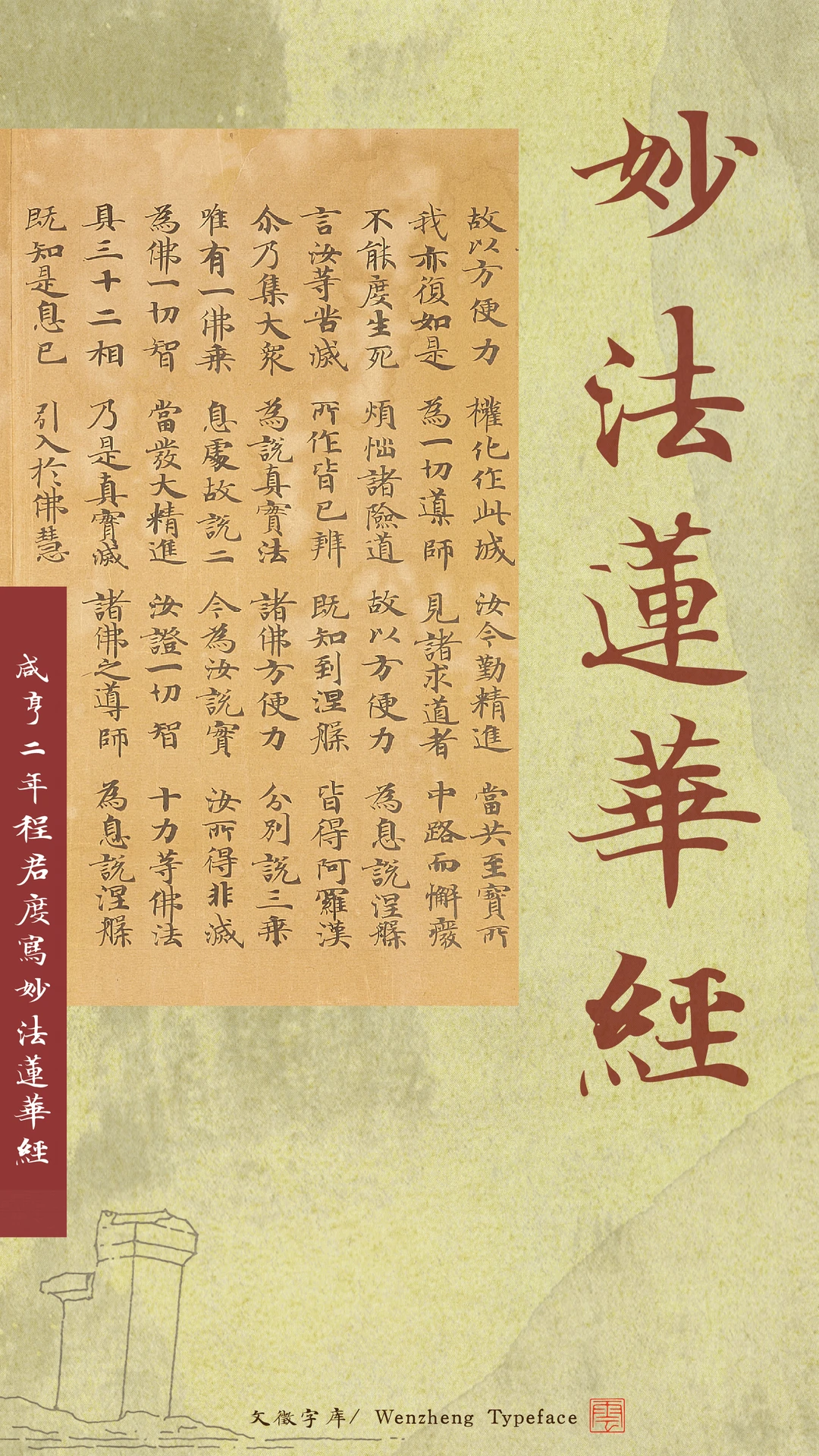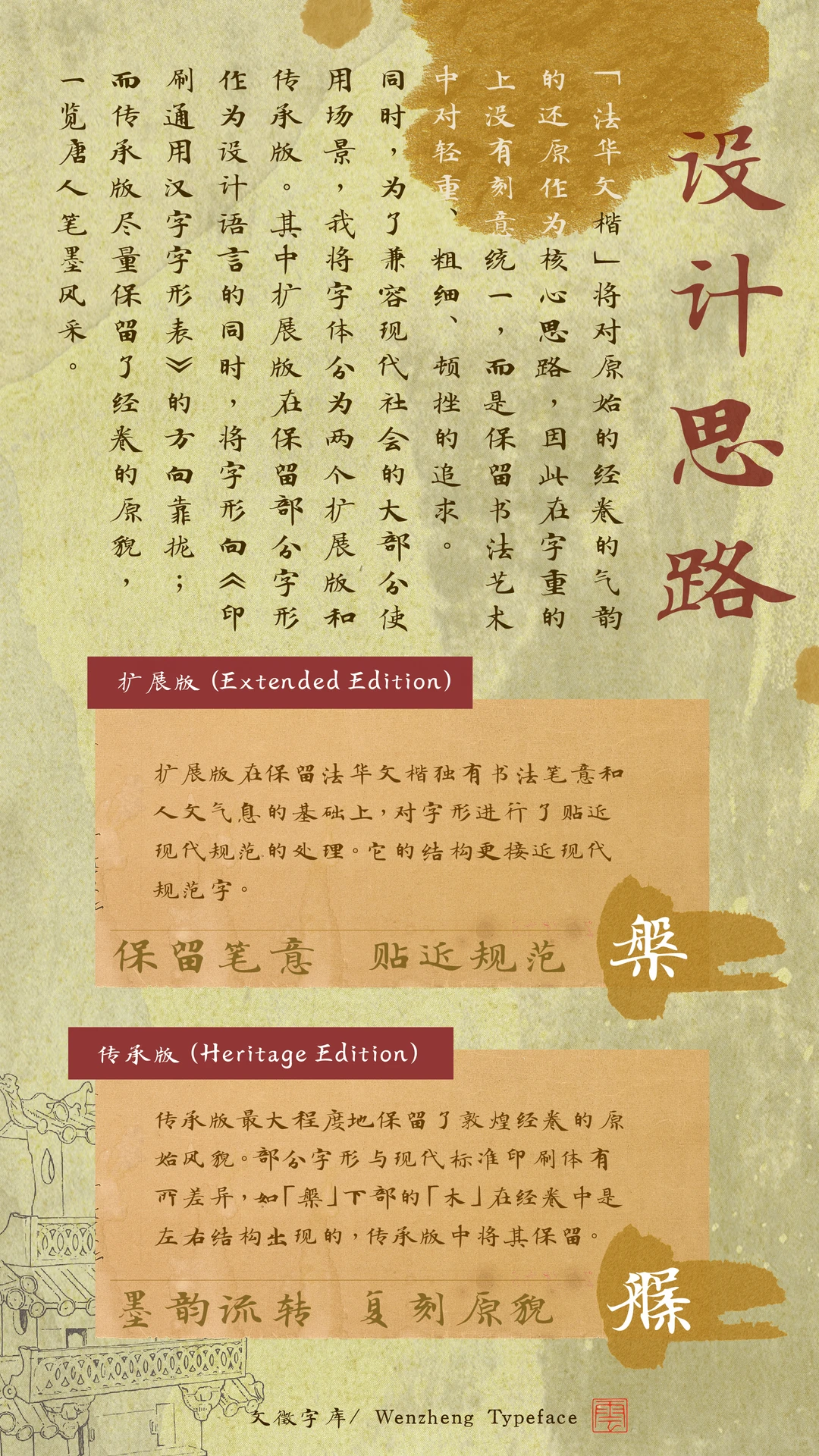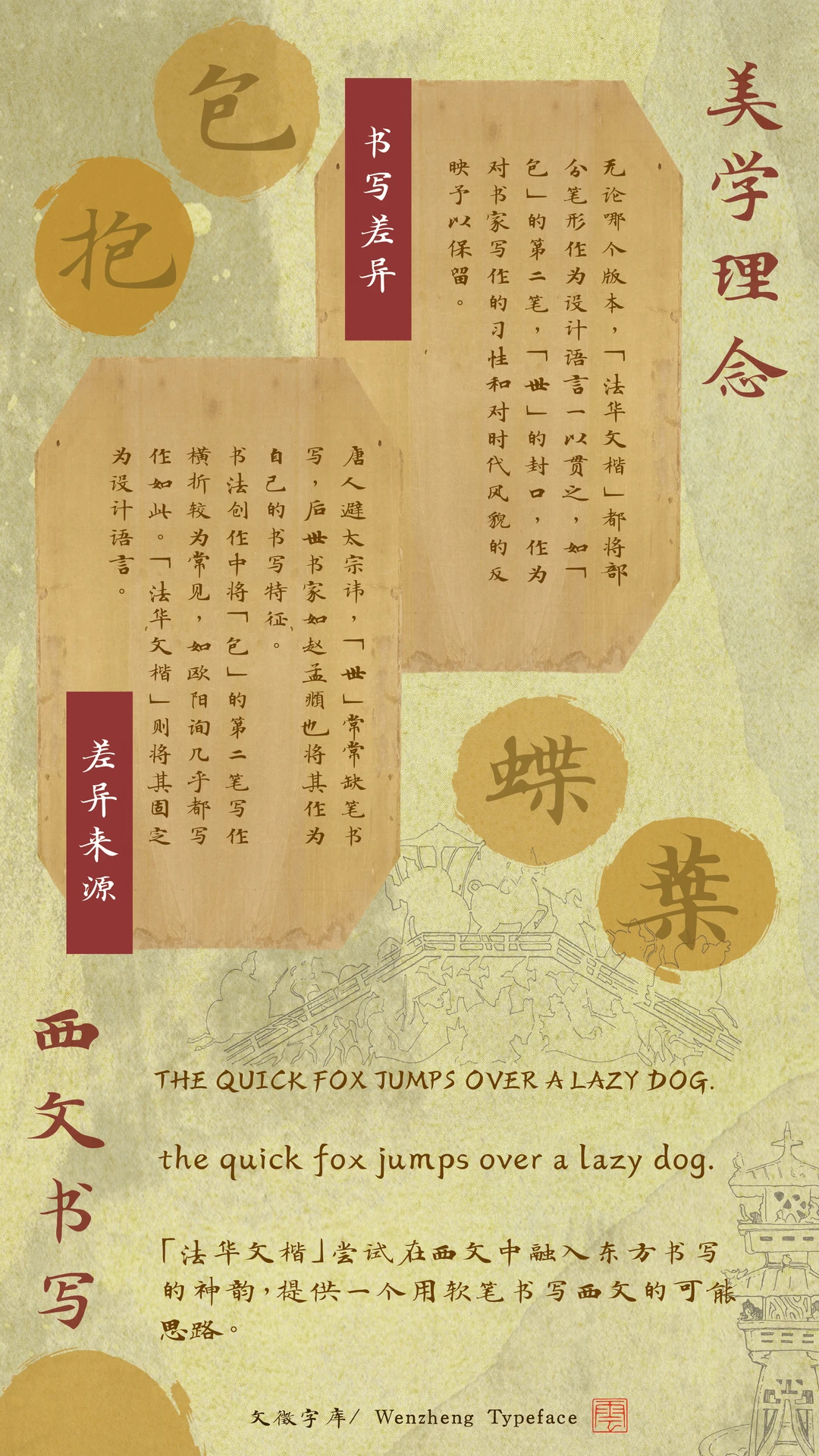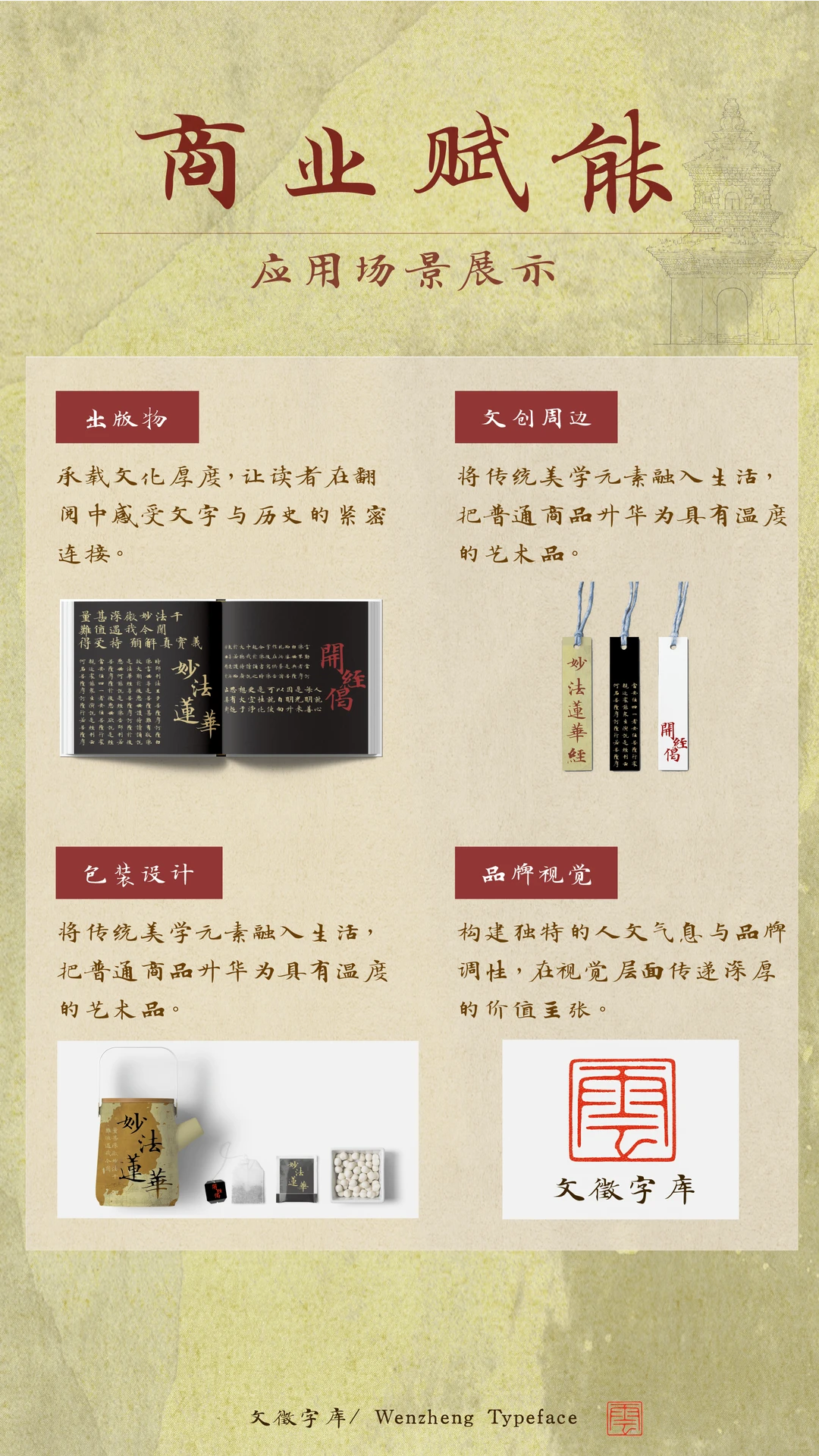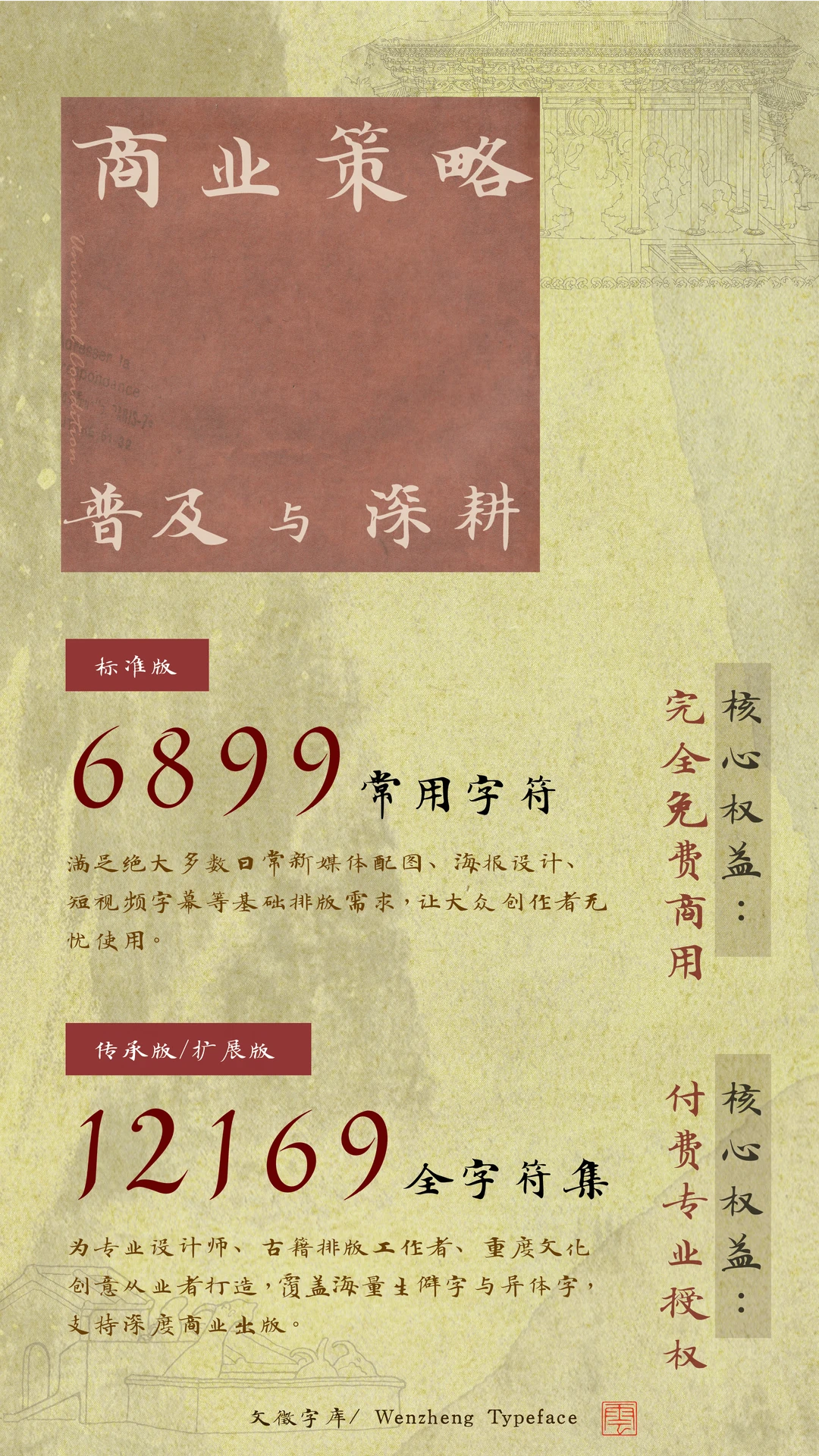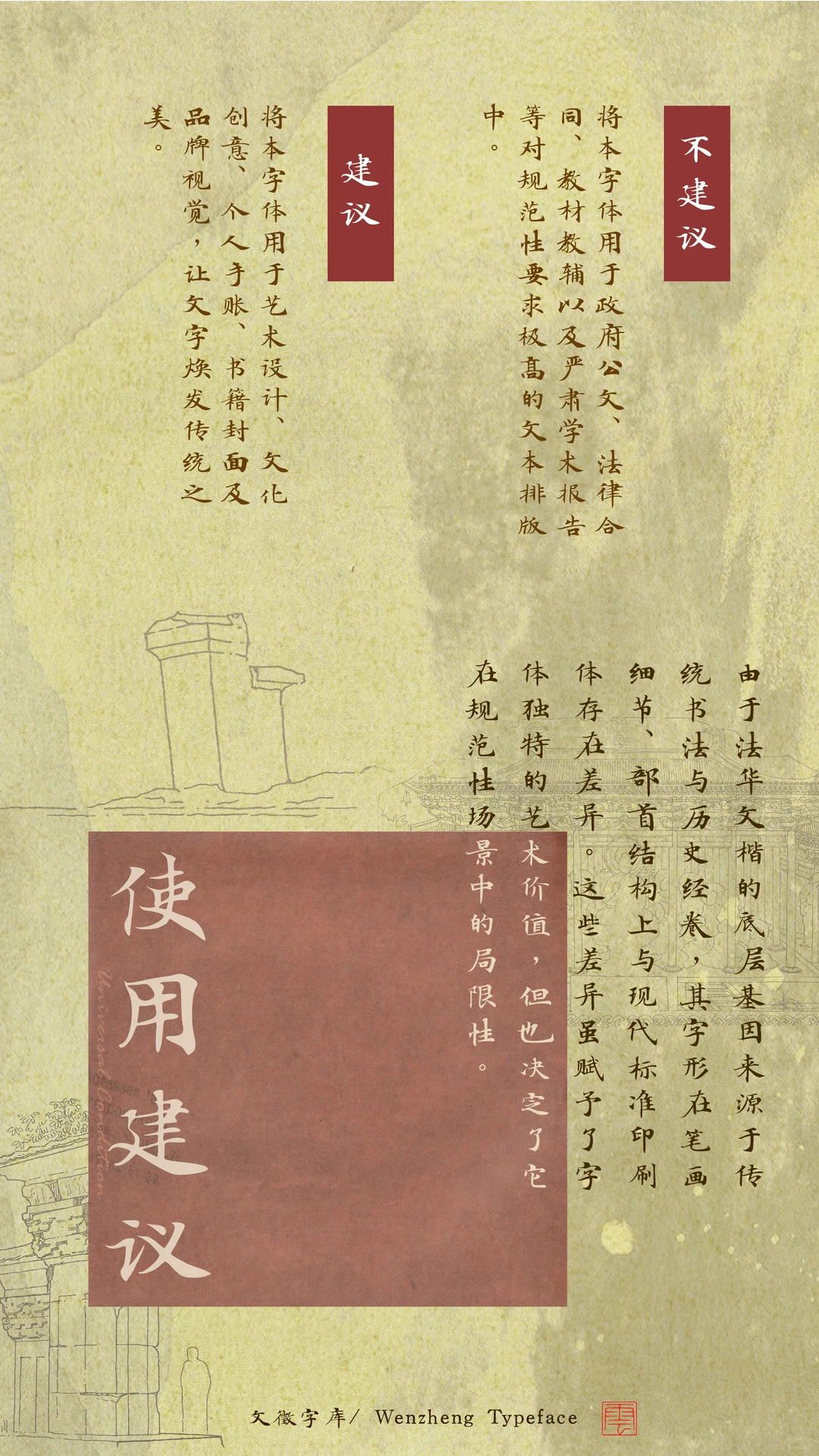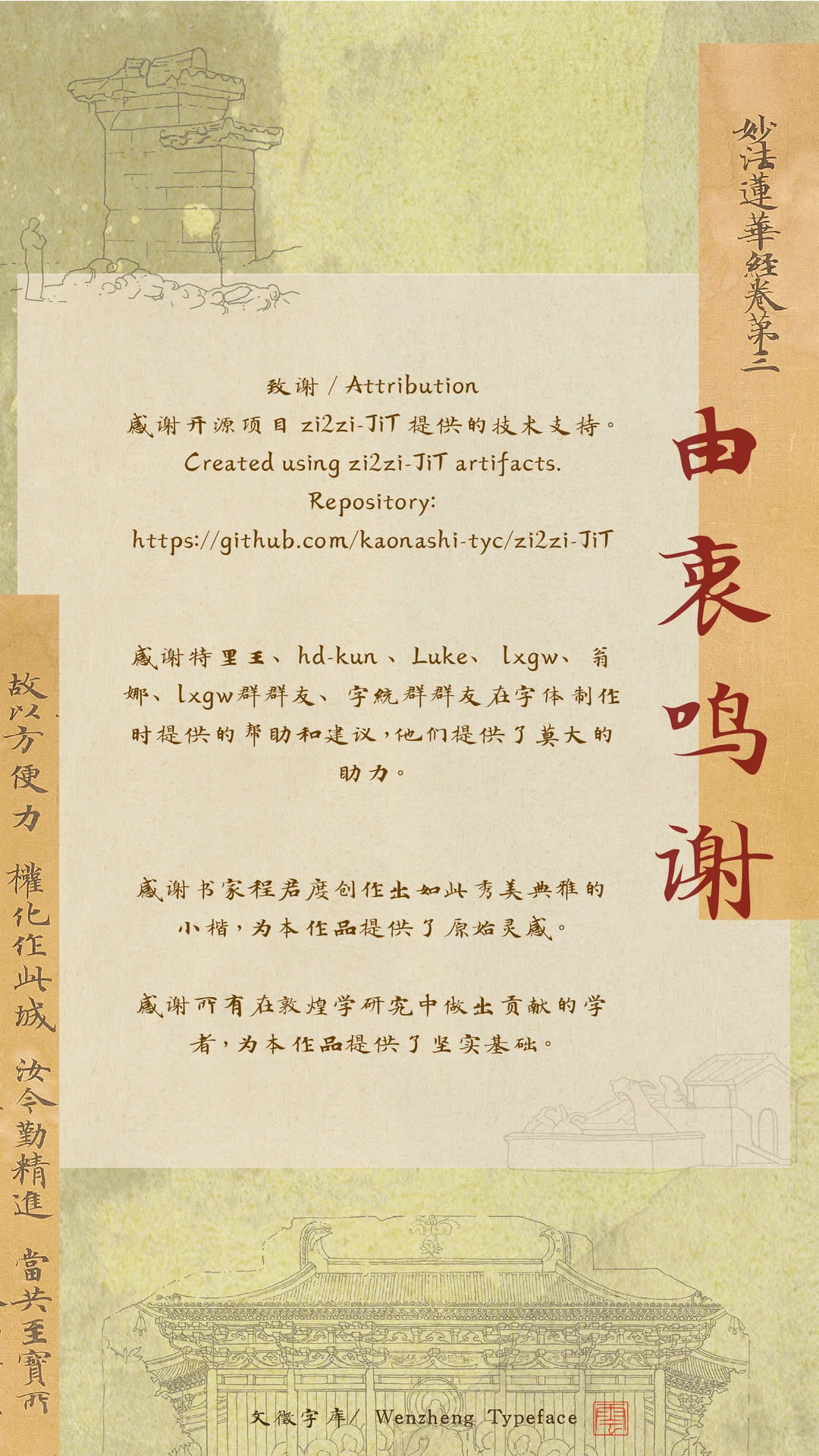
你是否还苦于没有让人耳目一新的免费楷体? 试试这款「法华文楷」,让你的封面质感瞬间拉满!
🚀 这是一款以敦煌经卷为灵感,具有唐人写经特征的字体 。
我特意做了两个版本,精准拿捏不同场景: 🎁 普通版(免费商用) 规格: 6899字符(覆盖基础常用字) 定位: 入门首选。满足日常海报、短视频字幕等基础需求,商业项目0负担 。 💎 付费完整版(解锁双字形) 规格: 12169字符(繁简生僻字全覆盖,告别豆腐块) 包含以下两款字形: 扩展版(现代感): 规范好读。结构向现代字形靠拢,适合长文排版和正文阅读 。 传承版(古艺术感): 极致复古。100%保留敦煌原帖异体字结构,笔墨韵味最浓,做艺术大标题绝了 !
💡 避坑小贴士:因为是书法字体,笔画和标准印刷体有差异,所以政府公文、合同这类严谨场合不建议用哦 !用在品牌视觉、手账、文创上才是它的正确打开方式!
文徵字库展示的《妙法莲华经》书法,右侧大字“妙法莲华经”,左侧为经文内容,落款咸亨二年程君度写妙法莲华经
设计思路:法华文楷字体扩展版保留书法笔意并贴近现代规范,传承版最大程度复刻敦煌经卷原貌。
文徵字库法华文楷字体设计图,介绍其保留传统书写特征的美学理念,并展示融入东方软笔神韵的西文书写示例。
商业赋能应用场景展示图,分为出版物、文创周边、包装设计和品牌视觉四个板块,
文徵字库法华文楷使用建议:推荐用于艺术设计、书籍封面等创意场景展现传统之美;不建议用于公文、合同等规范排版,因其字形源于传统书法,与现代标准印刷体存在差异。